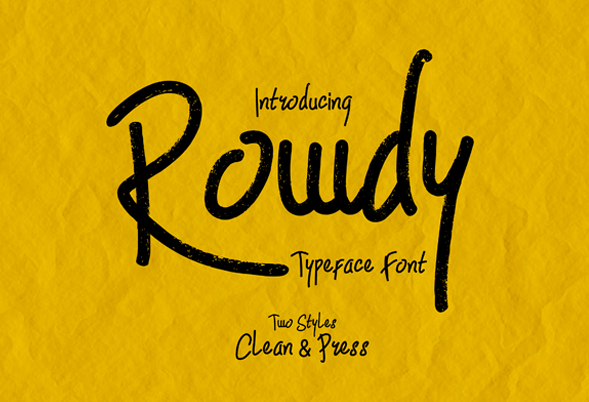
Rowdy Typeface – Download Grátis
A fonte Rowdy Typeface é uma escolha perfeita para aqueles que desejam adicionar um toque de personalidade aos seus projetos digitais. Ela foi criada por madeDeduk e é uma versão gratuita, ideal tanto para designers independentes quanto profissionais que procuram diversificar o seu portfólio com fontes únicas. Se você se encantou com as linhas modernas e desafiadoras de Rowdy Typeface e está curioso sobre sua versão completa, não hesite em dar uma olhada nos links abaixo. Você encontrará mais maravilhosas fontes criadas por madeDeduk no seu estúdio online (https://creativemarket.com/madeDeduk) e também na fontes gratuitas oferecidas pelo anggunsuandewi em sua loja de recursos (https://fontbundles.net/anggunsuandewi). Se você achar Rowdy Typeface tão inspiradora quanto nós, consideramos uma doação muito apreciada.